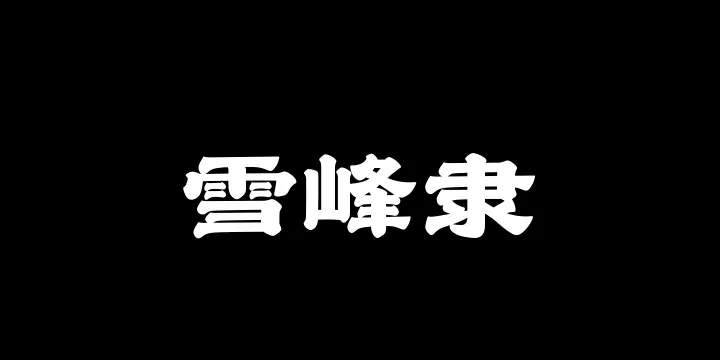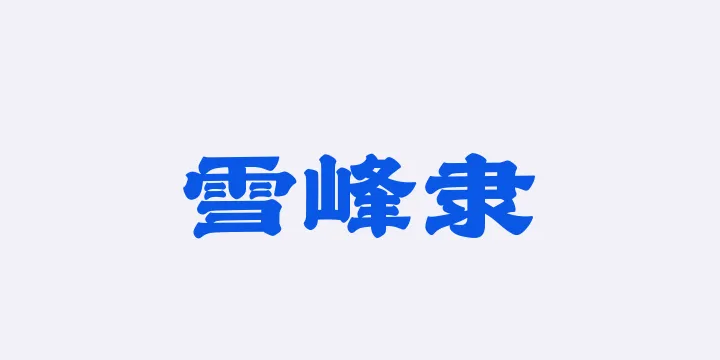
山海雪峰隶W By 山海字库 商用字体
字体全名: 山海雪峰隶W
字体简介: 山海雪峰隶,包含简繁汉字9169个,是一款带有隶书韵味的国潮风字体。该字体气吞山河,雄健有力。整体以隶书为骨,字形扁方,取正势,重心平稳,结体紧实,笔画铿锵有力,横平竖直,书写的顿笔风格强烈。该字体适合用于传统文化相关的使用场景,如时令节气、节日庆典、民俗特产等,也适用于新中式风格的品牌,彰显中华气韵。